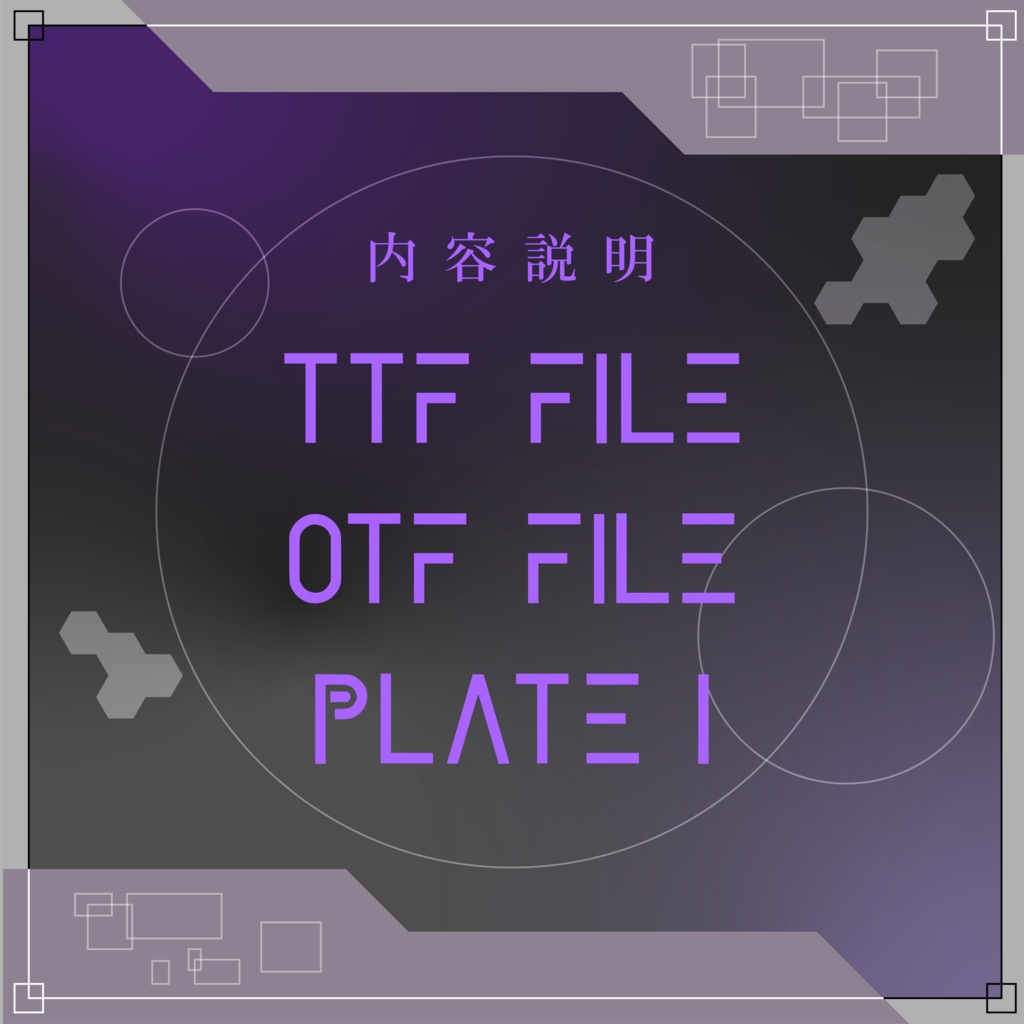
Public Sircle Font
◣◥ NEO TYPE FACE ◣◥ ◣◥◣◥ Public Sircle Font ◣◥◣◥ ◣◥◣◥◣◥ https://public-sircle.online/ ◣◥◣◥◣◥ ◣◥ 説明 ◣◥ こんにちは。 グラフィックアーティスト/デザイナーのxhi-_qhi(旧式)Art Lab.です。 今回ワタシが制作した"Public Sircle Font"に興味を持ってくださり、ありがとうございます。 今回ワタシがこのフォントを制作するにあたって意識したことは、おとなしさと扱いやすさです。 アルファベットの特徴を崩さずにシンプルな印象を作り上げることができたかなと思います。 ぜひご活用ください。 ◣◥◣◥ 商用利用について ◣◥◣◥ xhi-_qhi(旧式)Art Lab.の無料フォントについて 旧式アートラボ製フォントは一部例外(商用利用不可と明記)を除き、商用利用可能です。 できれば下記Twitterアカウントのフォローをしていただきたいです。 また、ご使用の際に特に明記していただきたい情報などはございませんので、ご安心ください。 これからもxhi-_qhi Art Lab.をよろしくお願いします。 ◣◥ ご依頼について ◣◥ お仕事の依頼は xhi.qhi.artwork@gmail.com もしくはツイッターダイレクトメッセージまでお願いします。 ◣◥ Twitter ◣◥ https://twitter.com/xhi_qhi © 2022 xhi-_qhi ART LAB.